漫画家 沖田×華先生 特別講演会「やらかしたっていいじゃん」
今回はフォント沼なお話ではなく、モリサワが取り組んでいる活動についてお伝えします。
モリサワは「文字を通じて社会に貢献する」という経営理念に基づき、「文字の視点」から性別、年齢、国籍、障害などの個性差を受け入れ、尊重される共生社会の実現、ダイバーシティの推進に取り組んでいます。
この活動の一環として、LD、ADHD、識字障害といった目に見えない障害と向き合いながら、自身の経験を赤裸々に公表し続ける漫画家の沖田×華先生、株式会社ぶんか社 第一編集部 編集長の花澤亜希子氏をお招きし、「障害への理解」をテーマに特別講演会を行いました。幼少期から現在に至るまで、乗り越えてきた苦労や、今でも苦手なことなどお話しいただきながら、モリサワフォントに抱いた印象やウエイトの違いで変化する見やすさについても伺いました。
沖田×華 おきた ばっか
漫画家。富山県出身。
小学4年生の時に医師よりLD(学習障害)とADHD(注意欠如・多動性障害)の診断を受ける。社会人になってからは、看護師、風俗嬢を経て2008年に漫画家デビュー。NHKでドラマにもなった『透明なゆりかご』(講談社)で第42回講談社漫画賞(少女部門)受賞。
自身の日々の失敗談を綴った『毎日やらかしてます』(ぶんか社)、終末期病棟が舞台の『お別れホスピタル』(小学館)など、話題作を連載中。
日常で感じる困難と対処法。読者に伝えたいこと。
― 沖田先生が診断を受けた障害は、いわゆる「発達障害」と呼ばれ、生まれつきの脳の働き方の違いにより、さまざまな特性があるそうですが、例えばどんな特性をお持ちなのでしょうか。
沖田×華先生(以下、沖田):学習障害(LD)の一つである識字障害(ディスレクシア)という字の読み書きが難しい特性があったりします。小学校の時から、書取りの練習を毎日させられても全く字がうまくならず。毎日のように親に怒られていました。今でも、漫画の原稿で、ちょっと難しい漢字は書けないので、アシスタントさんに書いてもらったりします。
花澤亜希子氏(以下、花澤):ネームでは漢字の間違いが多いですね。平仮名で書かれているところを漢字に直すといった修正もすることがあります。
― ご自身の生活でご苦労されていることはありますか?
沖田:締め切りはきちんと守っているつもりですが、打合わせの日をよく間違えてしまいます。実はこの講演会の打合わせも忘れていました(笑)。時間もよく間違えるので、ごまかせるように1時間前に着くようにしています。それから、初めて行く場所は、前日に周辺まで来て下見をしています。当日に迷って時間に遅れそうになると、パニックになってしまうので。知らないことがあるととても不安になるので、前もって情報を入れておかないとダメなんです。
漫画も、以前はページ数が急に増えたりするとパニックになっていました。当時は通常4〜6ページの連載をしていたんですが、突然違う出版社が「じゃあ今回16ページで」と言ってくる。すると「どうして私をこんなに困らせるの!?私のことをいじめているんだ!」と決めつけてしまって。その度に、同じく漫画家の夫が「それはお前の作品が面白いから仕事をくれているんだよ」と諭してくれたり。
― 予期していないことがあるとパニックになってしまうんですね。また、容貌失認という障害があると、漫画で拝見しました。
沖田:はい、そうです。他人のことは主に声で認識しています。冬は特に大変ですね。黒いダウンジャケットに帽子と、似たような恰好をしている人が多いので、夫婦でスーパーに行ってもちょっと離れると夫が分からなくなってしまうんです。最近も、夫と間違えて知らないおじいちゃんのカゴに卵を入れてしまいました(笑)
― 沖田先生を一番身近でみている花澤さんは、沖田先生のこうした特性をどう感じていらっしゃいますか?
花澤:初めてお会いした時は、「本当に障害があるのかな?」という印象でした。ところがある日、3〜4人で取材をしていた時、会話をしていてもうわの空だったんです。その後上がってきた原稿も、内容が全然違っていました。そこで3人以上になると会話が苦手なんだな、と気がつきましたね。
あとは、連絡事項が複数ある場合は、必ず一つずつ伝えるようにしています。お互い抜けがなく、伝わりやすいので。それから、電話での雑談中には、なるべくお願いごとをしないようにしています。代わりに、LINEやメールで文字に残していますね。
魅力的なところもたくさんあります。行動的だし、アイデアもどんどん出してくれます。本当に太陽みたいな方です。
― 作品の中で、たくさんの過去の出来事が細部まで描かれていますし、「頭の中に記憶の引き出しがある」というお話もありました。
沖田:はい。現在、5作品くらい連載があるんですが、漫画のジャンルによって、記憶のあり方が違うんです。
例えば「やらかしシリーズ」の場合は、小さい頃の記憶を使っています。どうして昔の細かい記憶があるかというと、子どもの頃、自分が見た面白い話をすると友達と楽しく会話ができるということに気づいたんです。それが自分の家族の話で、うちの親の恥ずかしいことを全部記憶するようにしていました。いわゆる映像記憶というもので、今でもその時のことは、天気や服装まで、昨日のことのように思い出せます。一方で、毎日のようにやらかしているエピソードはすぐ忘れちゃうので、その場ですぐに絵にしたり、Twitterに投稿したりして、それを思い返しながら原稿にしています。
『お別れホスピタル』(小学館)は部屋のようなイメージです。ドアをノックして開けたら、これからネームにする患者さんのデータが、クローゼットみたいにブワッと並んでいます。
例えば、80歳の患者さんの50歳当時の話を取り上げようと思ったら、その人の人型の束を一つ取るんです。その人型は80枚の紙が重なっていて、その束の50枚目の紙をちぎって漫画に描いている感じですね。その部屋にはファックスもあって、友達から聞いたエピソードなどが送られてきています。
『透明なゆりかご』(講談社)は、ドアを開けたら海ですね。延々と続く潮干狩りをしているイメージです。「すくったら泥!またすくっても泥!ネタが無い!」みたいな。これは本当に大変です。
― 看護師をされていたご経験があるということですが、その際にご自身の特性で困った点などはありましたか?
沖田:私は高校を卒業してすぐ准看護師の免許を取って、4年間くらい小児科に勤めていました。仕事自体は楽しかったんですが、学生時代と比べると、社会に出てからの学習障害の特性の出方がまったく違っていましたね。
職場では、それぞれの人間関係をきちんと把握していないと仕事に支障が出るんです。ところが就職した時には、私はそれを理解していませんでした。例えば、同僚の陰口をそのまま本人に伝えて、病院の人間関係を悪化させてしまったりとか。あと掃除中に、衝動的に落書きをしたくなって、使っていたハイターで壁に自分の名前を書いてしまったり。院長夫人に「どうしてこんなことやったの!」と怒られました。でも理由がないから答えられなくて。わざと困らせていると勘違いされて、嫌がらせをされるようになったんです。
そうして結果的に看護師を辞めることになりました。仕事も職場もとても好きだったので、それさえなければ看護師を辞めていなかったと思います。
― 人の気持ちを理解しにくいということで、日々何か工夫していることはありますか?
沖田:夫と暮らして17年目になるんですが、一緒に住んで最初の10年くらいはずっと喧嘩していたんです。ですが、11年目からは、夫の性格を受け入れられるようになりました。
夫は相談ごとが多いんですが、例えば「仕事を辞めようと思っている」「辞めたらいいんじゃない」みたいな話し合いをした次の日に、「やっぱり続けようと思う」と言い出したりするんです。そうすると私は途端にブチ切れてしまうんですよね。「昨日の話し合いはなんだったのー!」って。相談に乗った相手の意見が変わってしまうと、それを聞いてきた自分の時間が無駄になると思っていたんです。
でも、段々と、そういう愚痴を言える人が私しかいないってことに気がつきました。なので、話を聞こうとするポーズを習得しましたね。自分に関係ない話とは思いつつも、きちんと合いの手を入れられるようになりました。そうすると、不思議と喧嘩しなくなるんですよね。
― 作中で「対人マニュアル」を作ったエピソードがありましたが、どういった内容ですか?
沖田:私は、一緒に仕事をしている人との関係性を間違えて、友達の延長みたいになってしまったりすることがあるんです。例えば、原稿に直しが入って、その時に忙しい状況だと、途端にムカッときてしまう時があって。「なんでこんな忙しい時に、こんな面倒臭いこと言ってくるんだ!」みたいな。「私が嫌いだからこういうことをするんだ」っていう被害妄想に入ってしまいがちなんです。
そこで、「編集は友達じゃありません」とか「私のことが嫌いだけど、イヤイヤ付き合ってくれているんだ」とか、あえて強い言葉を書き、インプットするようにしたんです。そうすると、修正が入った時も「私のことが嫌いなのにわざわざ言ってくれたということは、これは本当にやらなくちゃいけない仕事なんだな」と思えるようになったりして。
昔、花澤さんが異動するかもって話になった時に、「私もついていきます!それがたとえ小説でもファッション誌でも!」って大騒ぎしてしまいました。マニュアルを作る以前は、そうやって、担当さんに迷惑をかけることが度々あったんですよね……花澤さんが辞めちゃったら今でも泣きますけどね(笑)
花澤:(笑) でもやっぱり、線引きはしっかりされている先生だと思いますね。おしゃべりしていても、仕事の話になると顔つきが変わるというか。そういうところは、やっぱりプロだなと思います。
―「やらかしシリーズ」で読者にどんなことを伝えたいですか?
沖田:発達障害への認知というものが昔に比べてすごく広まっていますよね。たまに、知人から「自分の子どもが発達障害だけどどうしたらいい?」という相談を受けることもあるんですが、対処の方法は一概には言えないんです。本当に十人十色なので。だから、答えられないんですが、あまり悲観的にならないでいいですよ、と伝えたいです。当事者って意外と悲観的に思ってないんですよ。親の方が不安になったり可哀想と思ったりする。
そのきっかけや参考として、この本が読まれていったら嬉しいですね。
識字障害と文字。モリサワフォントはどう見える?
様々なフォントをご覧いただき、ウエイトの違いで変化する見やすさや、「A1ゴシック」や「竹」など、先生がそれぞれのフォントに抱いた印象についてご紹介します。
― 識字障害をお持ちの方は、線の強弱やはね、はらいがあると文字を見間違えてしまうという特性があるそうです。そこで、縦線が太く、横線が細く作られている明朝体(黎ミン)を使って、漫画の中でも取り上げられた「嬢」の漢字を用意いたしました。一番見やすいのはどれですか?
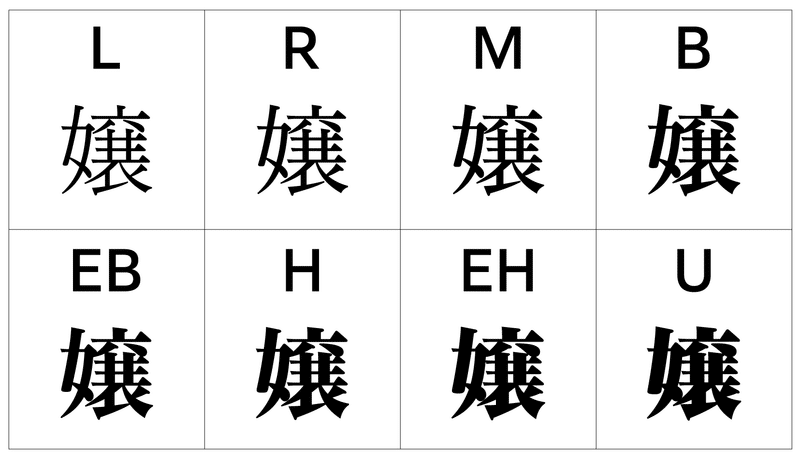
沖田:L、R、Mは読めますね。中でもRとMは、書けと言われればぎりぎりですが模写できます。Bからは難しいですね……。字が太いと線同士がくっつきだして、形がボワっとして、横線が何本かわかりません。4本にも見えるし、5本にも見えるんです。書くのは自信がないかな。
学生の頃、電子辞書でどんなに拡大しても、明朝体だったらその字を書くことができませんでした。顔くらいに拡大して、一本ずつ線の数を数えても、その数を記憶できなかったり。でもある日、夫がボールペンで書いた字をスッと読めたことがあって。たぶんボールペンは線の太さや強弱がないので、問題なく読めたんですよね。字の形がいろいろあるということを、そこで初めて意識しました。
― 続いて、フォントにどのような印象を持つか教えてください。いくつかのフォントで「×華のやらかし日記」というテキストを用意しました。
沖田:字を見るとき、面白いかどうかという基準で見てしまうのですが、そう考えると……
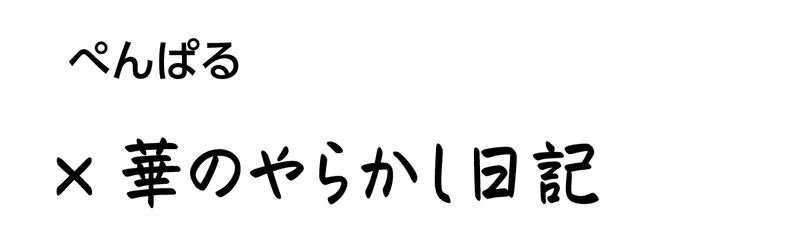
ぺんぱる
これは面白いですね。「し」が「く」みたいに見えます。こういう「し」でもいいんだって思いました。たまに私が書く字に似ています。
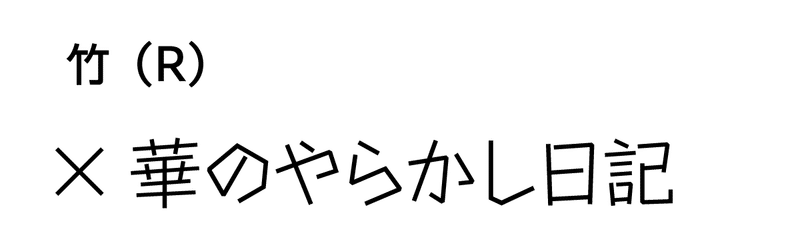
竹
これが一番好きですね。
(テキストが書いてある紙を振りながら)文字がカチャカチャ動いて見えます。なんだか音付きで見えてしまうんですよね。線が針金で作られたように、おもちゃっぽく見えますね。そのせいもあってか、なぜか銀色にも見えます。
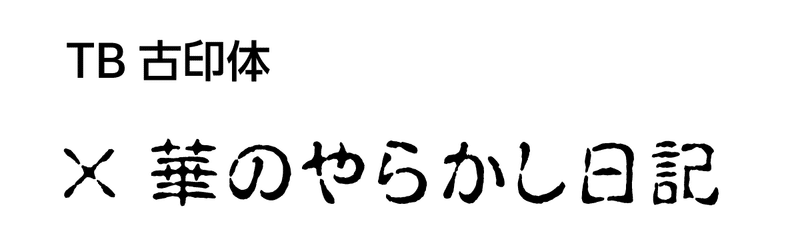
TB古印体
怖いですね(笑)
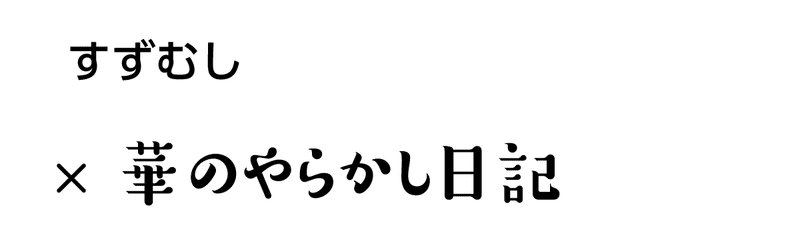
すずむし
読めるけど書けません。「華」は、線が何本かまったくわからないです。
勘亭流
拍子木みたいな木の音が聞こえます。「竹」もそうですが、たまに音付きのものがありますね。
プリティー桃
スナックっぽくていいですよね。桃って書いてあるからか、ピンクっぽく見えます。
陽炎
「か」「し」がわかりづらいですね。平仮名はやっぱり、書体によってわかりづらいですね。
― 以前打ち合わせでお伺いした時は、「A1ゴシック」が読みやすいとおっしゃっていましたね。
沖田:そうですね、見やすいし書きやすい。私、横線が多い字をどんどん大きく書いてしまう傾向があるんですが、「A1ゴシック」だったらたぶん、同じスペースで書けそうです。線の強弱がポイントだと思います。
― 文字を見て色や音を感じると言うのは面白いですね。
沖田:以前テレビで見たんですが、発達障害の学生の中には、参考書に色が多いと見づらくて使えないという人がいるそうです。シンプルで白黒なものじゃないと勉強しづらいと言うケースもあるみたいですよ。
― 識字障害を抱え、今までどのようなご苦労がありましたか?
沖田:小学校6年生までは、文章のまとまりが書けませんでした。なのになぜか「ペンパル部」(文通する部活)に入ってしまって、苦労しましたね。「あ」「ぬ」「ん」「ね」が極端に書けなかったので、親に何回も練習させられていたんですけど、全然書けるようにならなくて。最終的に友達に「50円あげるから手紙書いて」ってお願いするようになったんです。そうしたらとても気持ちが楽になりました。
親や教師からは、「真面目に努力すればできるにようになる」としか教わってこなかったんですが、無理だったので、できないことは誰かにやってもらえばいいやって思うようになりました。結局相手の親にバレて注意されちゃうんですけど(笑)
― 識字障害の認知度が上がってきたと思いますが、沖田先生はどうお考えでしょうか?
沖田:識字障害って一つじゃないということがわかりました。文字が一部反転して見えたり、文字が水彩画のように滲んで見えてしまったり、人によっていろんな見え方があるらしくて。
あるテレビの特集で、実際に識字障害の人が見ている文字の見え方(震えていたり、一文字だけどこかに飛んで行ってしまったり)をPCで再現して見たことがありました。その時、「ああ!私も同じ見え方だ!」と思いました。学生の時って、文字がどう見えづらいのかを言葉にできないんですよね。それで本当に苦労するし、読むことを諦めてしまう。他人から、怠けているとか真面目に勉強していないと言われることもあると思います。
でも今は、個人個人にあった教え方にどんどん変わってきているらしいです。きっとこれからも、認知や向き合い方がもっと変わっていくんじゃないかな。
発達障害を理解して、特性を前向きに捉える。
― 先生の漫画で、「これは自分の特性だから仕方ないか」と、状況や人の気持ちなどを受け入れるシーンがありますよね。「もっと自分のことを理解してほしい!」と腹を立てることはないのでしょうか?
沖田:理解してほしいというよりは、どうやったら怒られないで済むのかということしか考えていませんでした。私は困っていないのに、自分以外の人が困っている状況ばかりだったから、自分が悪いんだと思っていました。自分が悪いと強く思っていたので、周囲に腹を立てることはなかったですね。子供の時って、自分が何に困っているかわかっていないんですよね。だから親や周囲の大人も、広く意見を聞いて、発達障害に対する理解を深めた方がいいのかなと思います。
― 最後に同じように目に見えない障害を抱えている方にアドバイスをお願いします。
沖田:モリサワさんに出会って、ものすごく膨大な数の字の形があるとことに驚いたと同時に、文字って残るものなんだ、ということがとてもよくわかりました。
もし、障害を抱えていることで、例えば今、文字の読み書きが苦手だったとしても、「この文字って面白いな」と興味を持つことがとても大事だと思うんです。字を書くことが嫌だと嘆くのではなく、この文字の形面白いな、真似したいな、と思いながら、遊びの延長みたいに感じることも大切なのかなと思います。
そうやって、書ける・書けない、読める・読めない、それ以外のところで文字に対する関心を持って欲しいと思います。
一口に発達障害と言っても、困難さを抱えるシーンは本当にさまざま。自身の特性を前向きにとらえ、のびのびと生きようとする沖田×華さん。そして、先生の特性を理解し的確にサポートする花澤さん。どんな困難を抱えている人も心地よく過ごしていけるように、共生社会の実現に向けたヒントがたくさん詰まった講演会となりました。
モリサワは、多くの人が障害への理解を深め、一人ひとりが自分らしく生きていける共生社会の実現を目指して、これからも文字を通じた社会貢献に取り組んでまいります。